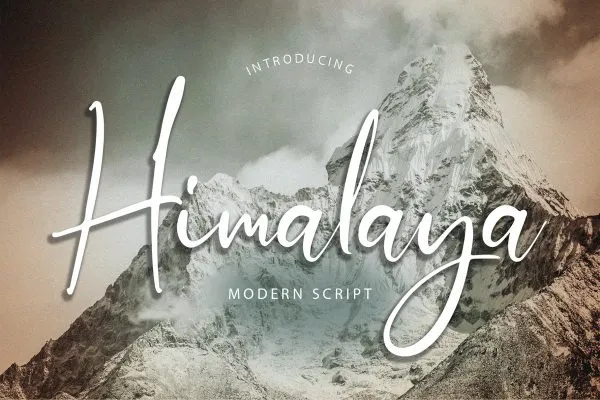
A fonte Himalaya é uma elegante tipografia script que foi cuidadosamente criada por Denny Subagja. Perfeita para uma variedade de projetos, incluindo criação de marcas, logotipos, designs de casamento, posts nas mídias sociais, anúncios, embalagens de produtos, design de camisetas, etiquetas, fotografia e até mesmo marcos. A sua forma elegante faz da fonte Himalaya um recurso visual perfeito para qualquer projeto que necessite de uma letra atraente e sofisticada. Ideal tanto para iniciantes quanto para profissionais, esta font pode transformar o seu trabalho em design de gráfica em algo único e impecável. Não importa qual seja o seu próximo desafio criativo, Himalaya está aqui para fornecer um novo olhar para qualquer projeto que você esteja planejando.